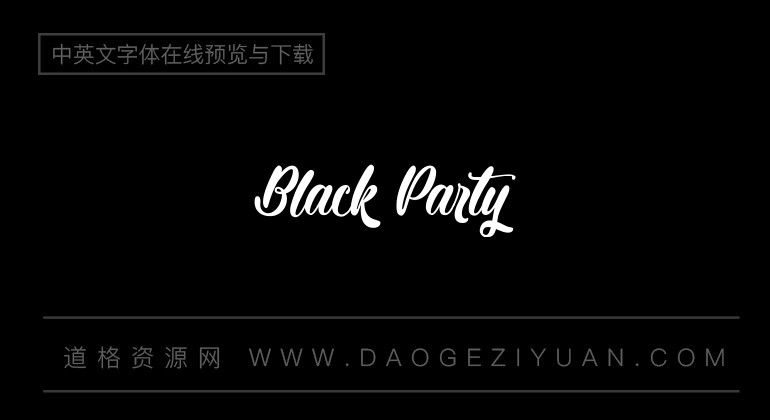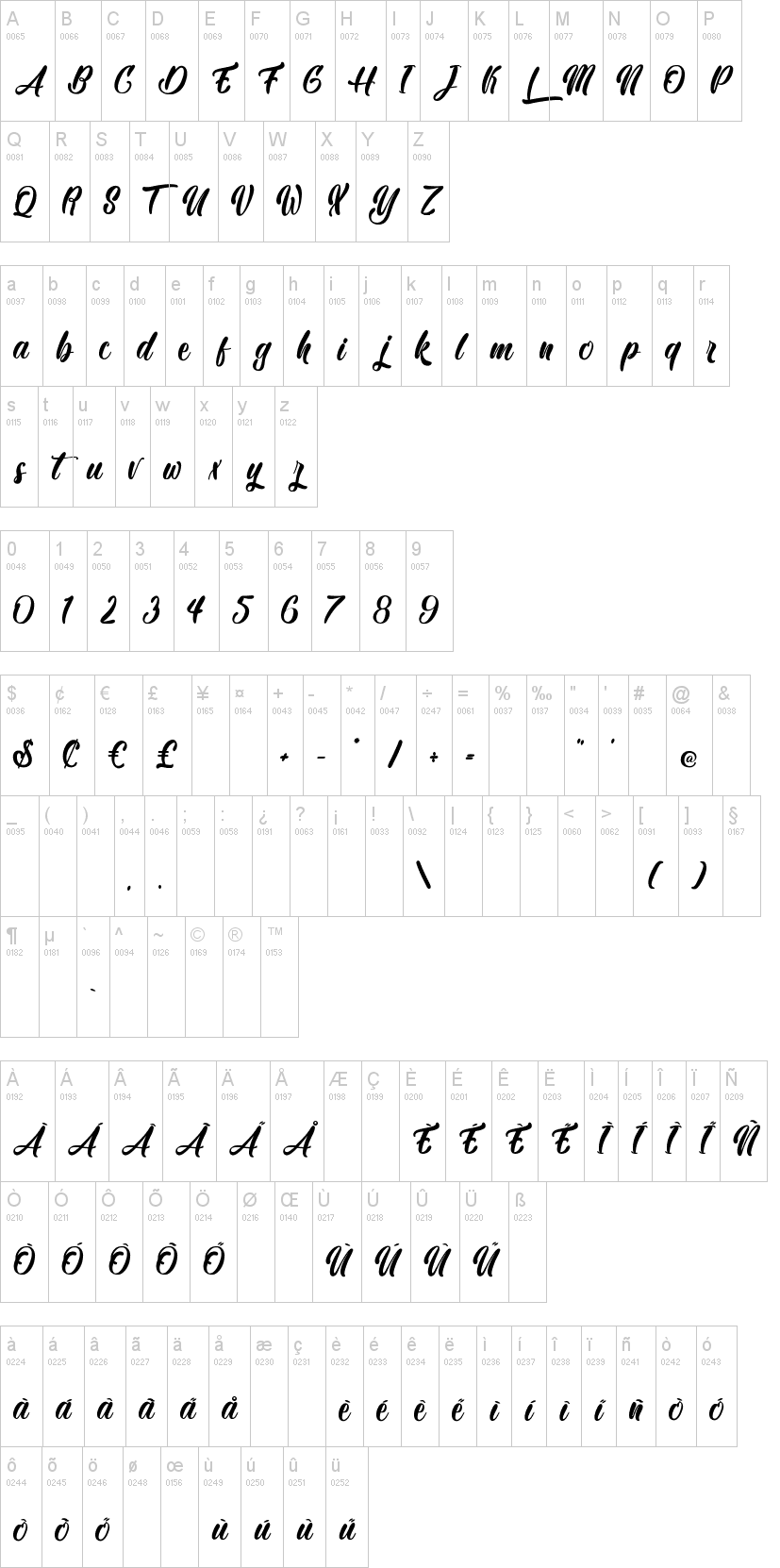
Black Party
Black Party 字体是一款具有现代感的英文字体,它拥有细节丰富的字体设计,具有清晰的细节和强烈的视觉冲击力。它的设计风格极具现代感,拥有大胆的字母形状,令人印象深刻。它的字母形状设计独特,有助于制作出有趣的文字效果。Black Party字体可以用于商业广告,海报,海报设计,标志,T恤等。
Black Party是一款非常不错的手写艺术字体,具有很好的视觉感,适合于文化类的宣传设计、商业类品牌的广告和产品包装设计以及个性化文字排版等较多场景。
Black Party字符映射图